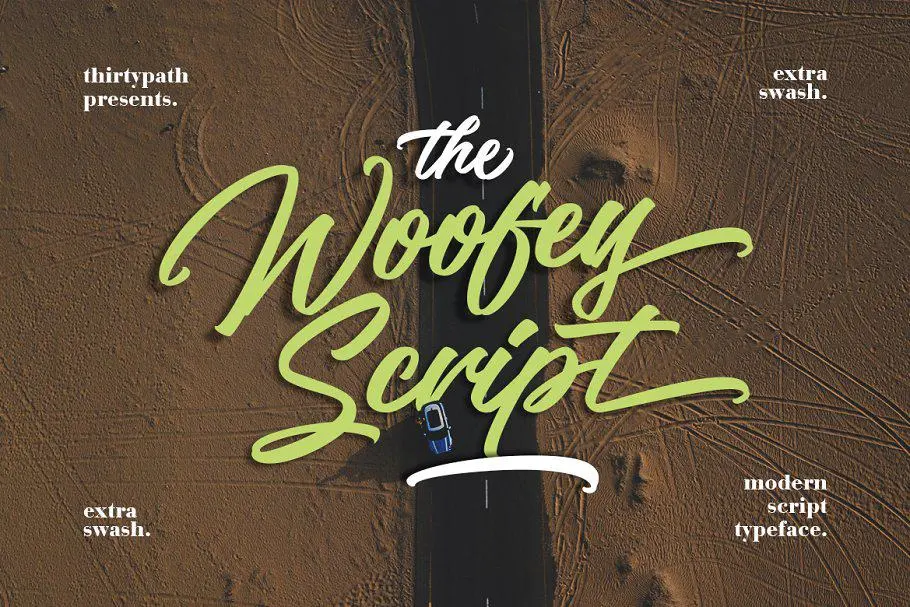
Aqui está uma descrição envolvente para a página de download da font ‘The Woofey Script Font’, respeitando os requisitos: O design contemporâneo de The Woofey Script Font é uma obra-prima criada pela thirtypath, apresentando um estilo que pode ser perfeitamente adaptado para uma ampla gama de projetos gráficos. Inspirado em letras feitas à mão, esta fonte cuidadosamente construída permite que seu texto brilhe ao maior acerto. Ideal tanto para textos como slogans ou posts de blog, a The Woofey Script Font também se adequará perfeitamente para design de materiais promocionais, desde cartazes até invitações e anúncios, atendendo aos mais variados requisitos gráficos. Com o moderno estilo da fonte, qualquer projeto pode ser transformado em algo único, tornando-se uma peça fundamental no seu kit de recursos gráficos. Não espere apenas para aprimorar sua apresentação visual, transforme-a em um trabalho de arte com The Woofey Script Font.